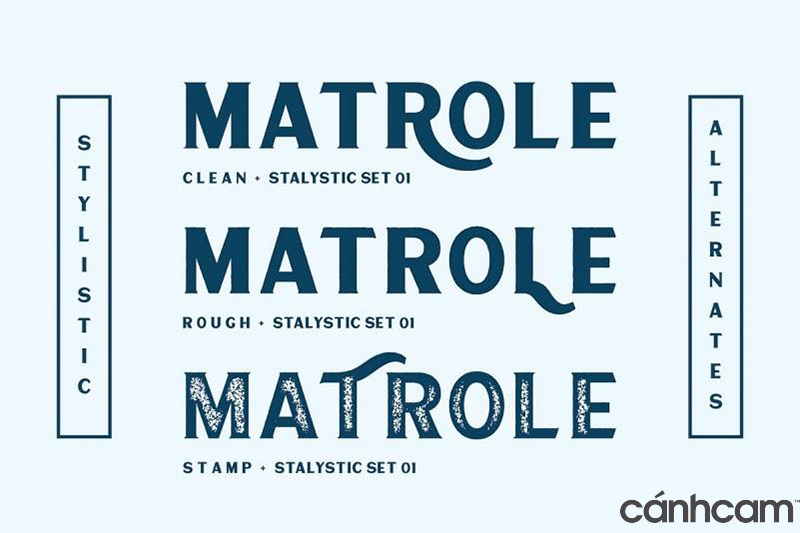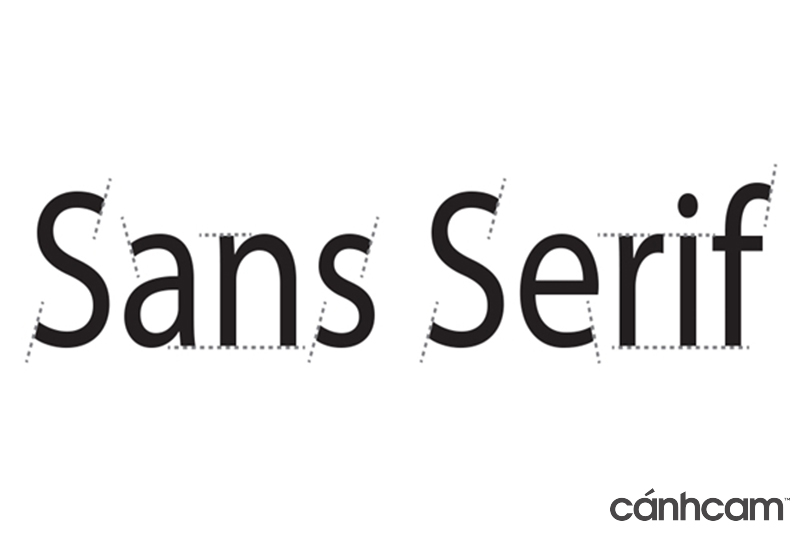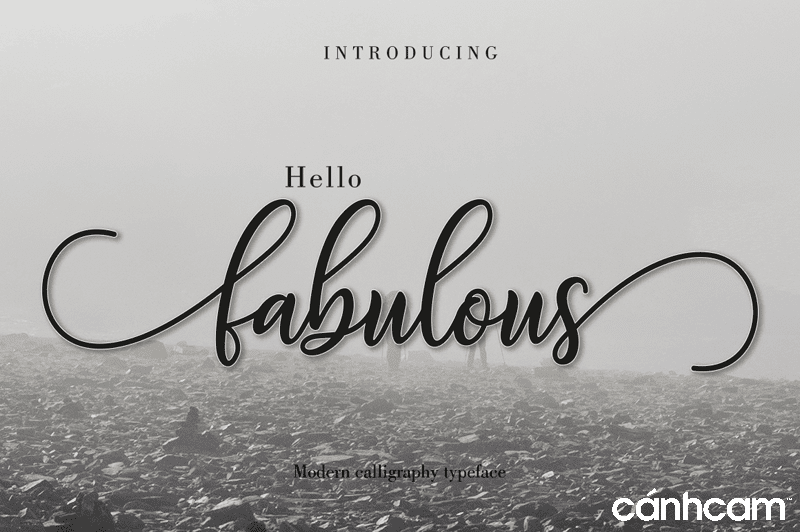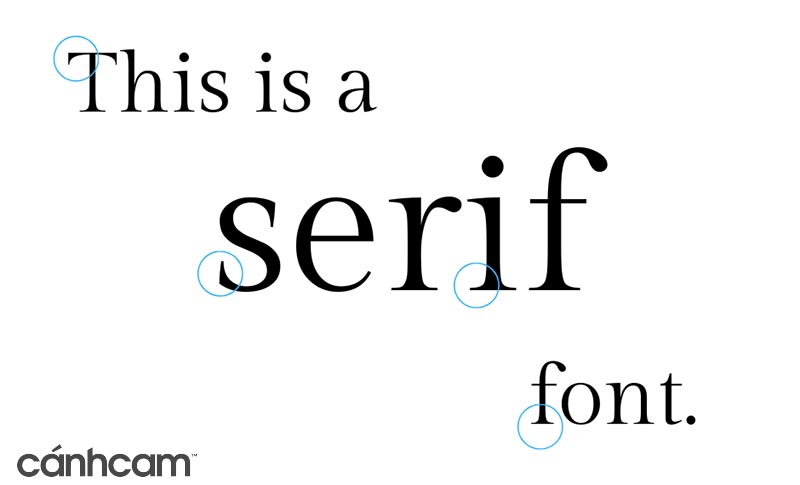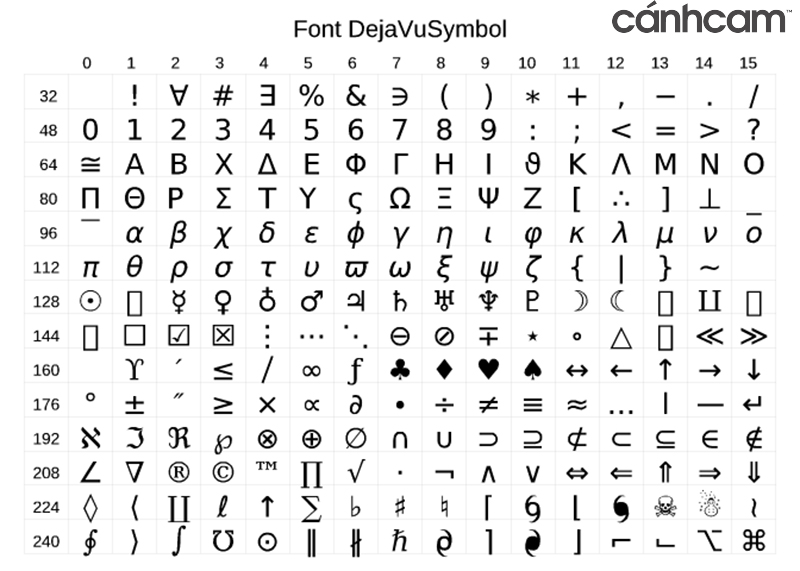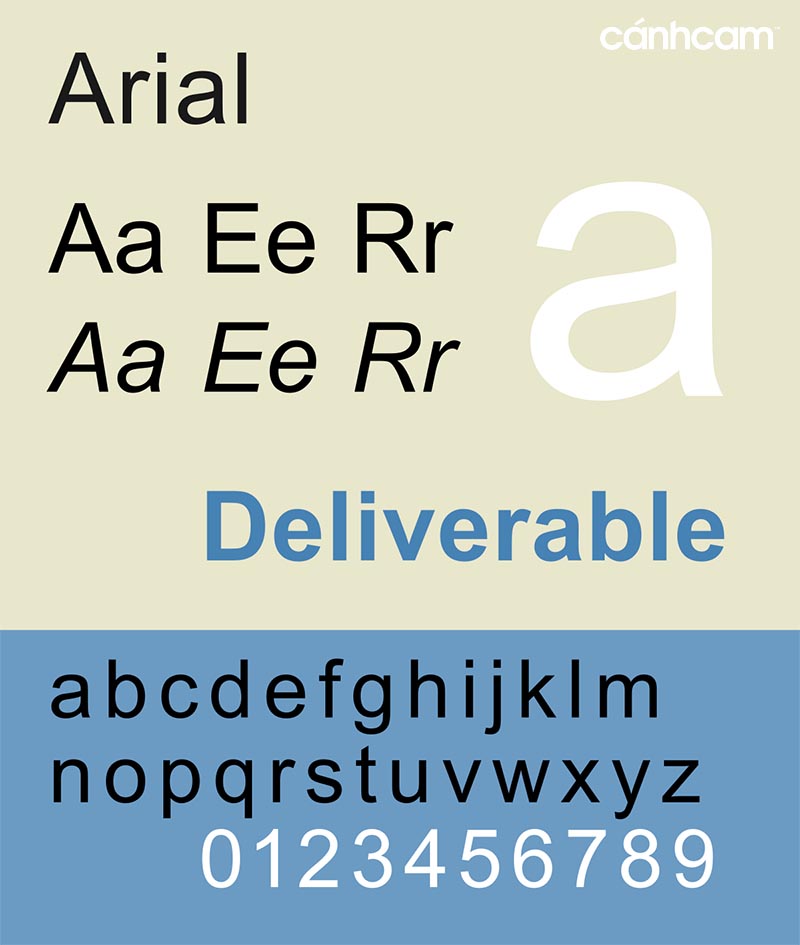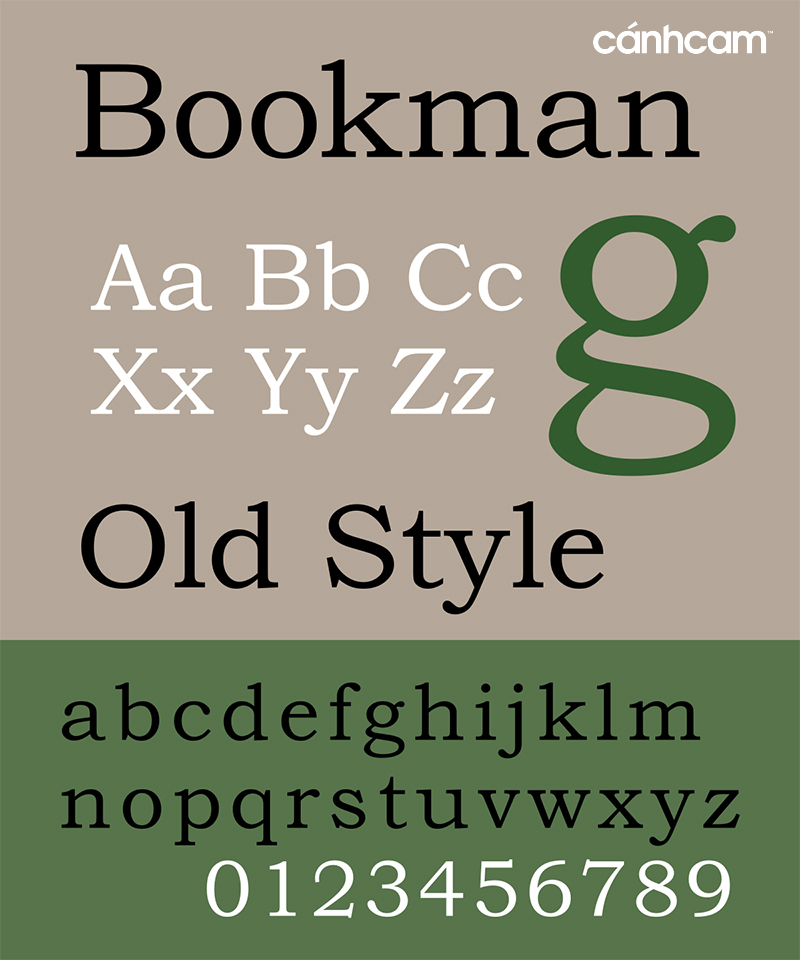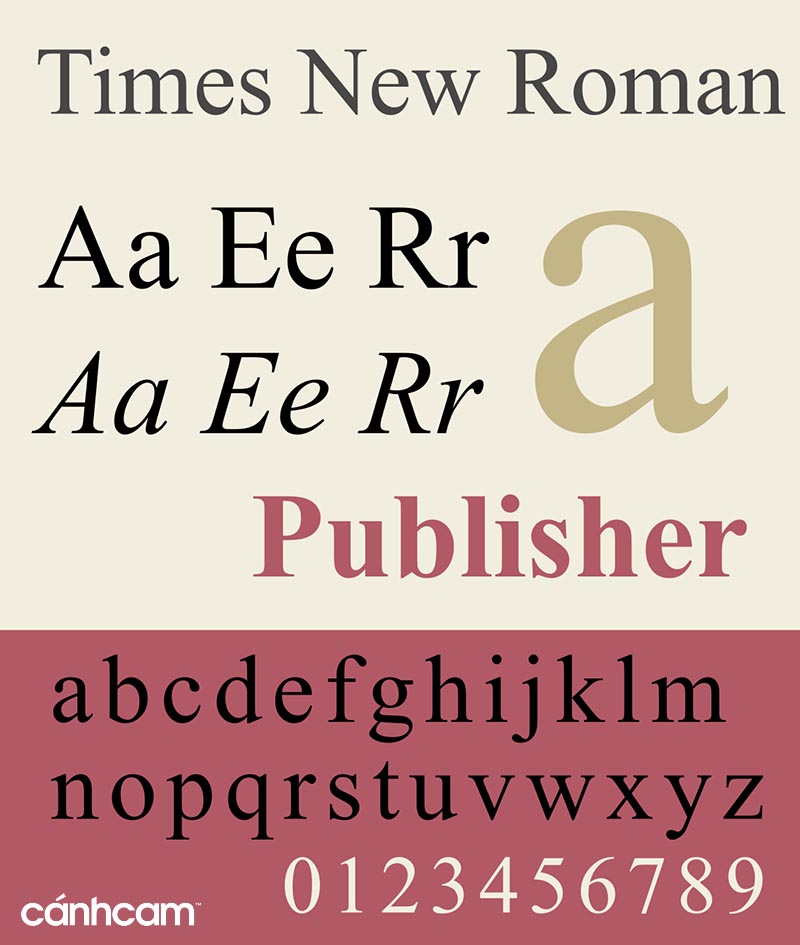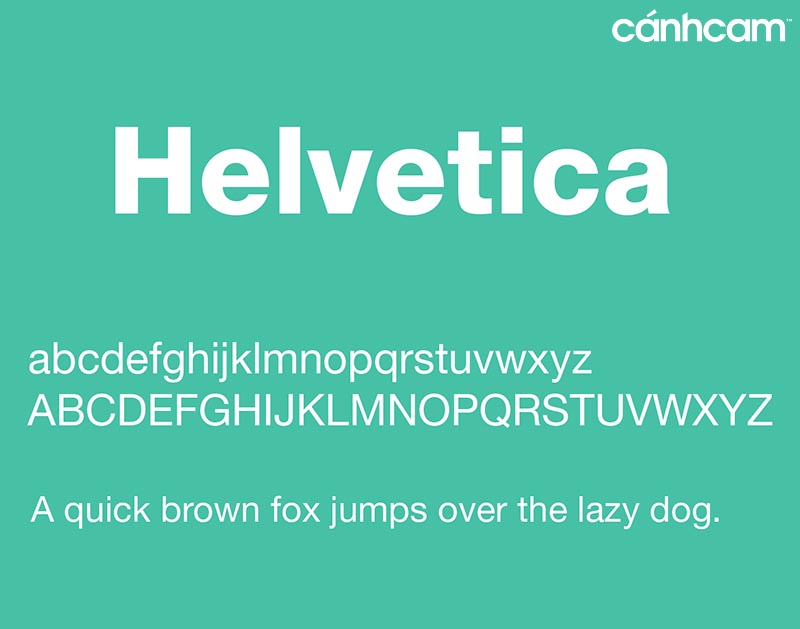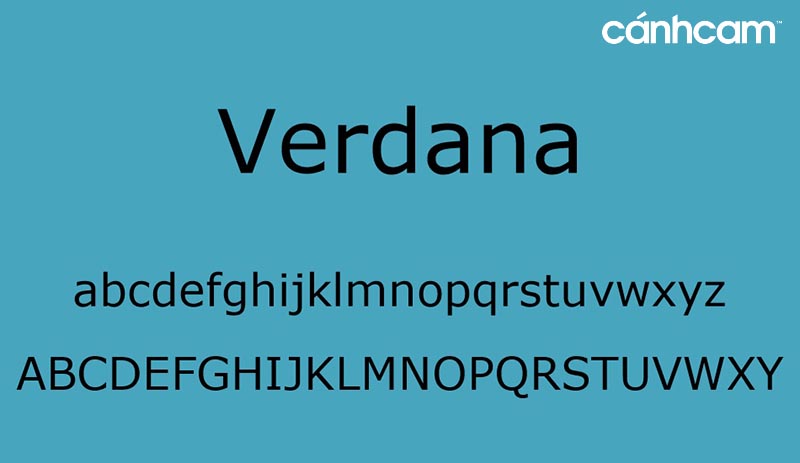
10 font chữ cho website đẹp & Lưu ý khi chọn
Trong quá trình thiết kế website chuyên nghiệp, ngoài việc xây dựng hình, bố cục chất lượng thì font chữ cũng là một yếu tố vô cùng quan trọng cần chú ý. Rất ít người biết rằng font chữ có thể ảnh hưởng đến cảm xúc của người xem. Do đó, biết cách chọn font chữ cho website phù hợp vừa giúp đảm bảo tính thẩm mỹ mà còn tăng sự chuyên nghiệp, đáng tin cậy hơn cho website cũng như chính doanh nghiệp. Trong bài viết sau đây chúng tôi sẽ chia sẻ đến bạn một số điều cơ bản và lưu ý khi chọn font chữ cùng các mẫu font chữ cho website đẹp nhất hiện nay.
Những nguyên tắc cần biết về font chữ khi thiết kế website
1.1 Phân biệt được font và typeface
Font hay phông chữ là bộ ký tự gồm các chữ cái, dấu câu, số và các ký tự đặc biệt khác có hình dạng, định dạng và kích thước xác định. Ví dụ Arial và Italic là 2 loại font khác nhau. Có thể hiểu đơn giản, font chính là một bộ các chữ cái thuộc 1 typeface nào đó với những hình dạng và định dạng riêng.
Typeface hay kiểu chữ, font-family, là gia đình của các cá chữ cái có chung thiết kế. Mỗi typeface sẽ tập hợp nhiều ký tự, mỗi ký tự đại diện cho chữ cái, số, dấu câu, biểu tượng,…. Nói chung lại, typeface là sự bao trùm của nhiều loại font, có định nghĩa rộng lớn hơn và không bị giới hạn về kích thước, hình dạng.
1.2 Phân loại font
1.2.1 Serif
Serif là chữ có chân, là font chữ có nét gạch ở đầu hoặc dưới dân một số ký tự. Serif là font chữ thường gặp trong các văn bản phổ thông do có tính dễ đọc.
1.2.2 Sans serif
Sans serif là chữ không chân, ngược lại với font Serif nó sẽ không có nét gạch trên đầu và dưới chân ở một số ký tự. Loại font này thường dùng làm chữ màn hình vì trông nhỏ gọn, hiện đại và đơn giản.
1.2.3 Symbol
Symbol là font chữ gồm các ký tự, biểu tượng đặc biệt, thường dùng để trang trí, minh họa, tượng trưng.
1.2.4 Display
Display là các font hiện đại có hình dáng riêng, thiết kế đặc biệt. Loại font này thường dùng trong trang trí, poster, làm biển quảng cáo,….
1.2.5 Script
Script là phông chữ dạng như chữ viết tay, thường có nét nối dài hoa mỹ, có thể nghiêng. Loại font này thường dùng cho các mẫu quảng cáo hiện đại, làm hình ảnh với những mục đích khác nhau.
Top font chữ tiếng Việt đẹp cho website
Hiện nay có rất nhiều loại font chữ khác nhau được sử dụng. Tuy nhiên, không phải font chữ nào cũng đẹp và cũng có thể dùng tiếng Việt. Nếu muốn thiết kế website với ngôn ngữ tiếng Việt thì chắc chắn bạn cần phải dùng font chữ tiếng Việt để đảm bảo cả về nội dung lẫn hình thức. Dưới đây chúng tôi sẽ giới thiệu đến bạn một số font chữ tiếng Việt đẹp cho website được dùng phổ biến nhất hiện nay.
2.1 Arial
Arial là font chữ cho website được dùng phổ biến nhất hiện nay bởi tính đơn giản, dễ nhìn. Font Arial là loại font được dùng nhiều trong nhóm Sans Serif, nó có thể dùng thay thế nhiều loại font chữ khác trên hệ điều hành windows.
2.2 Times New Roman
Có thể coi đây như là font chữ “quốc dân” bởi nó được dùng vô cùng phổ biến trong việc soạn thảo văn bản hiện nay. Times New Roman gần như là font mặc định trên windows, thích hợp dùng cho các trang báo chí, nội dung tài liệu,….
2.3 Helvetica
Helvetica thuộc loại font Sans Serif, chiều cao và khoảng cách giữa 2 ký tự gần như nhau. Font Helvetica thích hợp với kích thước chữ nhỏ nhưng vẫn đảm bảo tính dễ đọc với người dùng.
2.4 Courier new
Courier new cũng tương tự như Times New Roman, là font chữ quen thuộc với những người thường phải tiếp xúc với trình soạn thảo. Font Courier new được coi là sự lựa chọn tốt nhất khi viết nội dung hiện nay.
2.5 Verdana
Verdana là font đơn giản, khá dễ nhìn, tạo được cảm giác thân thiện cho người đọc. Chính vì điều này mà font Verdana được dùng phổ biến trong thiết kế thực đơn nhà hàng với kích thước trung bình hoặc nhỏ.
2.6 Georgia
So với những font khác thì font Georgia có kích thước các ký tự lớn hơn. Do đó, loại font này thường chỉ dùng trong một số trường hợp đặc biệt. Ngoài ra, không nên dùng font Georgia cùng lúc với font Time New Roman bởi sẽ không tạo được sự hòa hợp ở 2 font này.
2.7 Tahoma
Đây là loại font rất thông dụng để thể hiện nội dung trên website hiện nay. Font Tahoma có thiết kế đơn giản, rõ ràng, dễ nhìn, mang đến cảm giác nhẹ nhàng, dễ thu hút người truy cập website hơn. Ngoài ra, bạn cũng có thể dùng font Tahoma để thiết kế bìa, trang trí,….
Có thể thấy, font chữ cho website rất đa dạng. Tuy nhiên, không phải loại font nào cũng phù hợp với website của bạn mà cần có sự chọn lựa và lưu ý khi thiết kế.